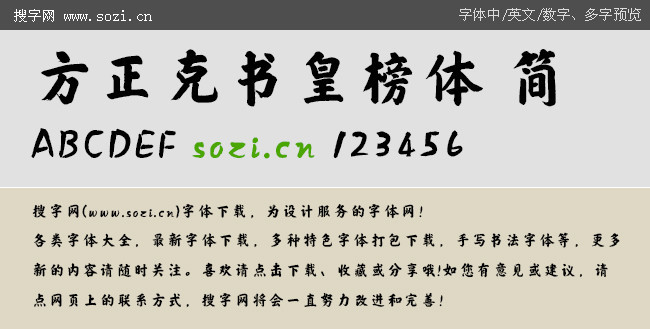
方正克書皇榜體-簡
搜字網(wǎng)提供一款方正克書皇榜體中文藝術(shù)字體下載,方正克書皇榜體字體設計以顏體多寶塔、勤禮為基底,融入了宮廷匾額的雍容、端正,求綿潤,綿中帶力。不張揚,不囂張,不做作,不浮夸,不求怪,不求險峻。與宮廷對聯(lián)比較,單字縱向稍作收斂,求方正,便于橫豎排版。特別適用于對聯(lián)、門頭字號匾額、大海報;中國風的產(chǎn)品,中國傳統(tǒng)節(jié)日廣告等。